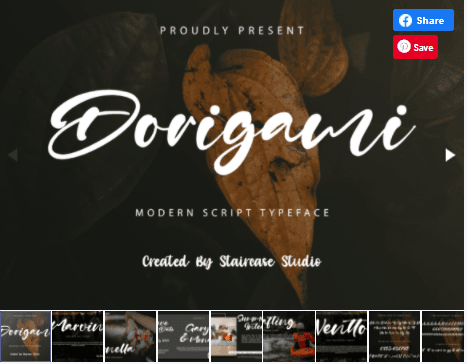
Dorigami Font
Доригами - это современный скриптовый шрифт, в котором есть набор букв и цифр, подходящий для любого из ваших творческих проектов. Он отлично работает с логотипами, дизайном брендов, цифровыми надписями, дизайном футболок / одежды, плакатами, журналами, вывесками, рекламой и многим другим!